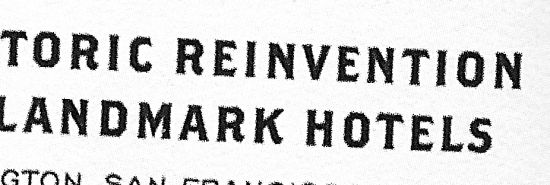
Amerikanerin mit schönen Beinen
hier wieder Futter für die menschlichen Suchmaschinen: Eine wahrscheinlich amerikanische Schrift mit außergewöhnlich charaktervollen Abstrichen:
Leider war die Vorlage sehr klein,deshalb schlechte Qualität: geht einfach einen Meter zurück, dann sieht man sie besser.